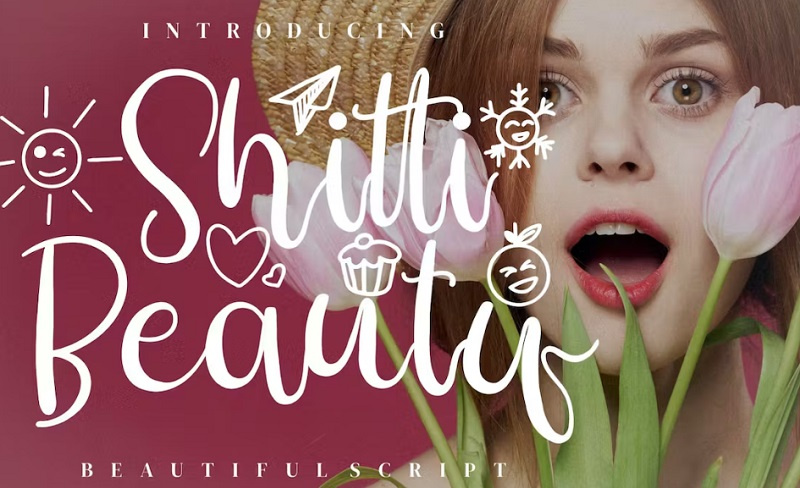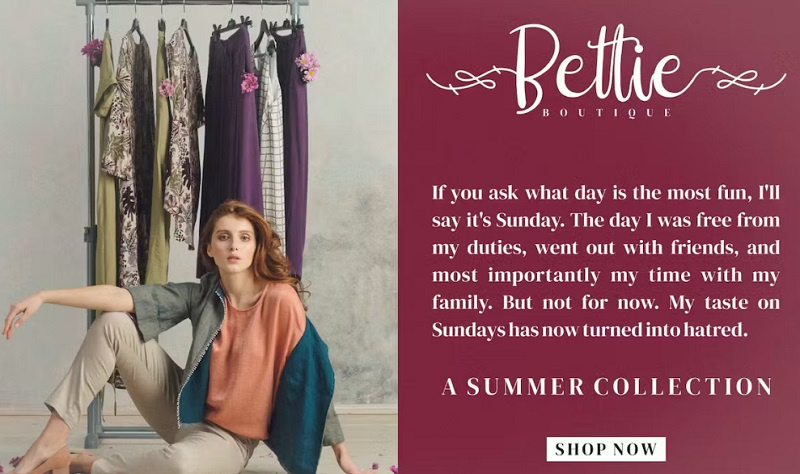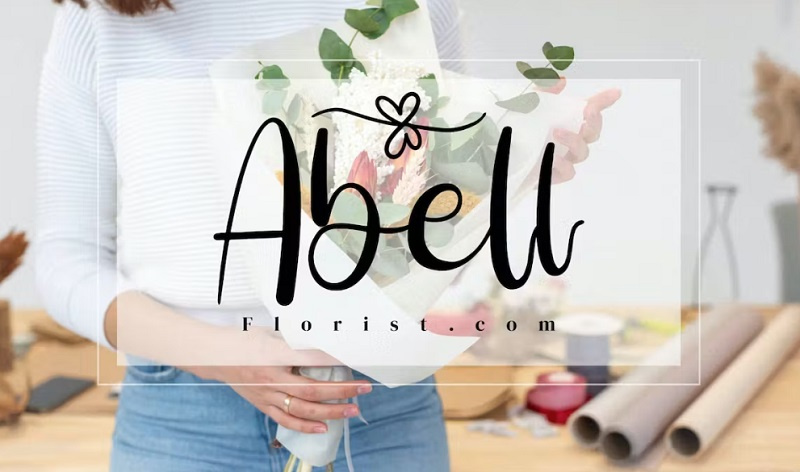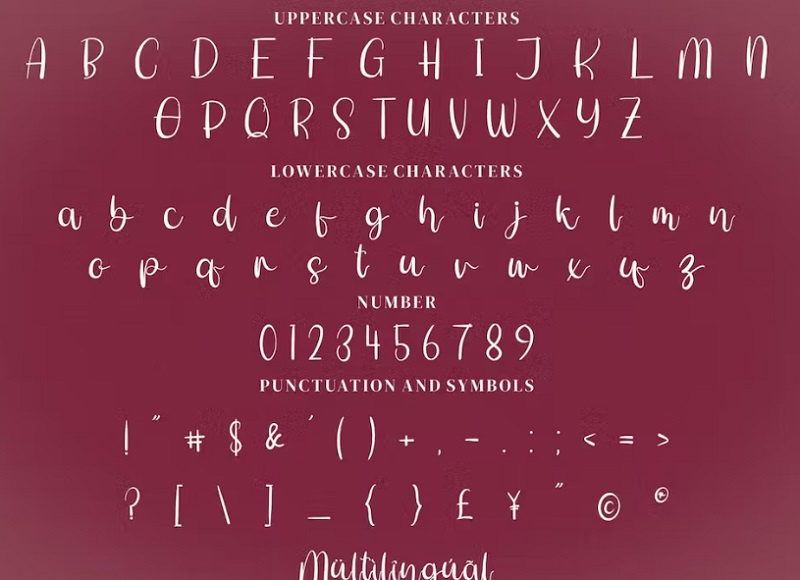
دانلود فونت انگلیسی Shitti Beauty یک فونت زیبا است، مناسب برای هر پروژه ای مانند: لوگو، پروژه های برندسازی، طراحی لوازم خانگی، بسته بندی محصول، لیوان، نقل قول، پوستر، کیف خرید، تی شرت، کتاب جلد، کارت نام، کارت دعوت، کارت تبریک، برچسب، عکاسی، واترمارک، رویدادهای خاص، و تمام پروژه های لوکس دیگر شما که نیاز به طعم و مزه امضای درجه یک دارند. برای دانلود فونت از جی اف ایکس دانلود به ادامه مطلب مراجعه کنید.